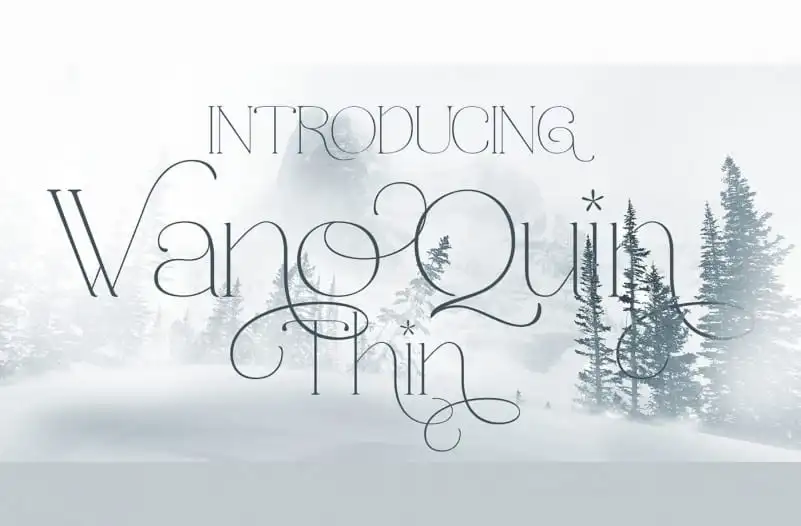
Wano Quin Serif Font – Download Grátis
A Wano Quin Serif Font é uma elegante tipografia serifada que traz uma sensação única e moderna à sua próxima criação visual. Essa fonte foi criada por Mix.Jpg e apresenta um amplo espectro de caracteres, incluindo um marcante índice especial e um conjunto numérico muito atraente. É perfeitamente adequada para uso em designs editoriais, embalagens de materiais de escritório e projetos de marca luxuosa. Suas linhas elegantes e detalhes sofisticados criam uma atmosfera moderna e atemporal ao mesmo tempo, tornando-a uma opção ideal para quem procura um estilo atraente e versátil. A Wano Quin Serif Font é uma escolha inteligente para qualquer designer que busca dar vida à sua marca através de um design visual impecável e sofisticado.